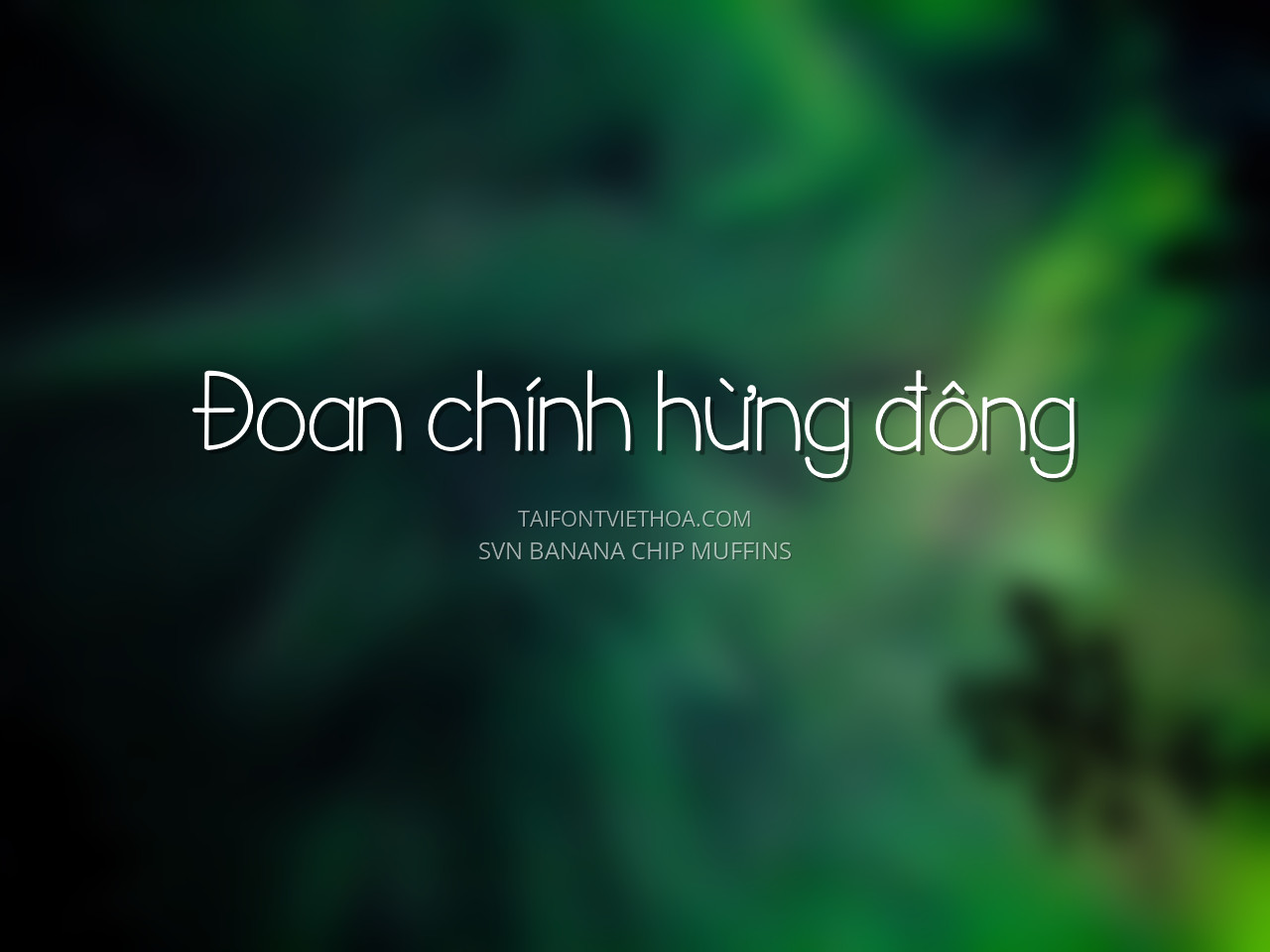
Font việt hóa SVN Banana Chip Muffins
Tác giả Font: Brielle Lang
Giới thiệu về font SVN Banana Chip Muffins – Kiểu chữ handwritten vui nhộn, thân thiện và sáng tạo
SVN Banana Chip Muffins là phiên bản Việt hóa của font Banana Chip Muffins – một kiểu chữ handwritten mang phong cách vui nhộn, thân thiện và đầy sáng tạo. Font được thiết kế với các nét chữ mềm mại, tự nhiên và biểu cảm, tạo cảm giác gần gũi và vui tươi, rất phù hợp cho các dự án thiết kế thiệp, poster, bài đăng mạng xã hội và các sản phẩm sáng tạo trẻ trung.
Thiết kế viết tay vui nhộn – Lý tưởng cho truyền thông trẻ và thiết kế sáng tạo
SVN Banana Chip Muffins sở hữu các nét chữ mềm mại, tự nhiên và biểu cảm, tạo nên cảm giác vui vẻ, sinh động và thu hút. Font rất phù hợp cho tiêu đề, bài đăng mạng xã hội, thiệp mời hoặc các sản phẩm thiết kế cần sự nổi bật và thân thiện. Phong cách thiết kế của Banana Chip Muffins rất thích hợp với các dự án truyền thông, giáo dục, giải trí và nghệ thuật.
Ứng dụng lý tưởng: thiết kế thiệp, bài đăng mạng xã hội, poster quảng cáo, bao bì sản phẩm, logo thương hiệu trẻ trung và các dự án sáng tạo cần phong cách năng động, vui tươi. Ngành nghề phù hợp: giáo dục, giải trí, truyền thông, nghệ thuật và các thương hiệu định vị theo phong cách trẻ trung, thân thiện.